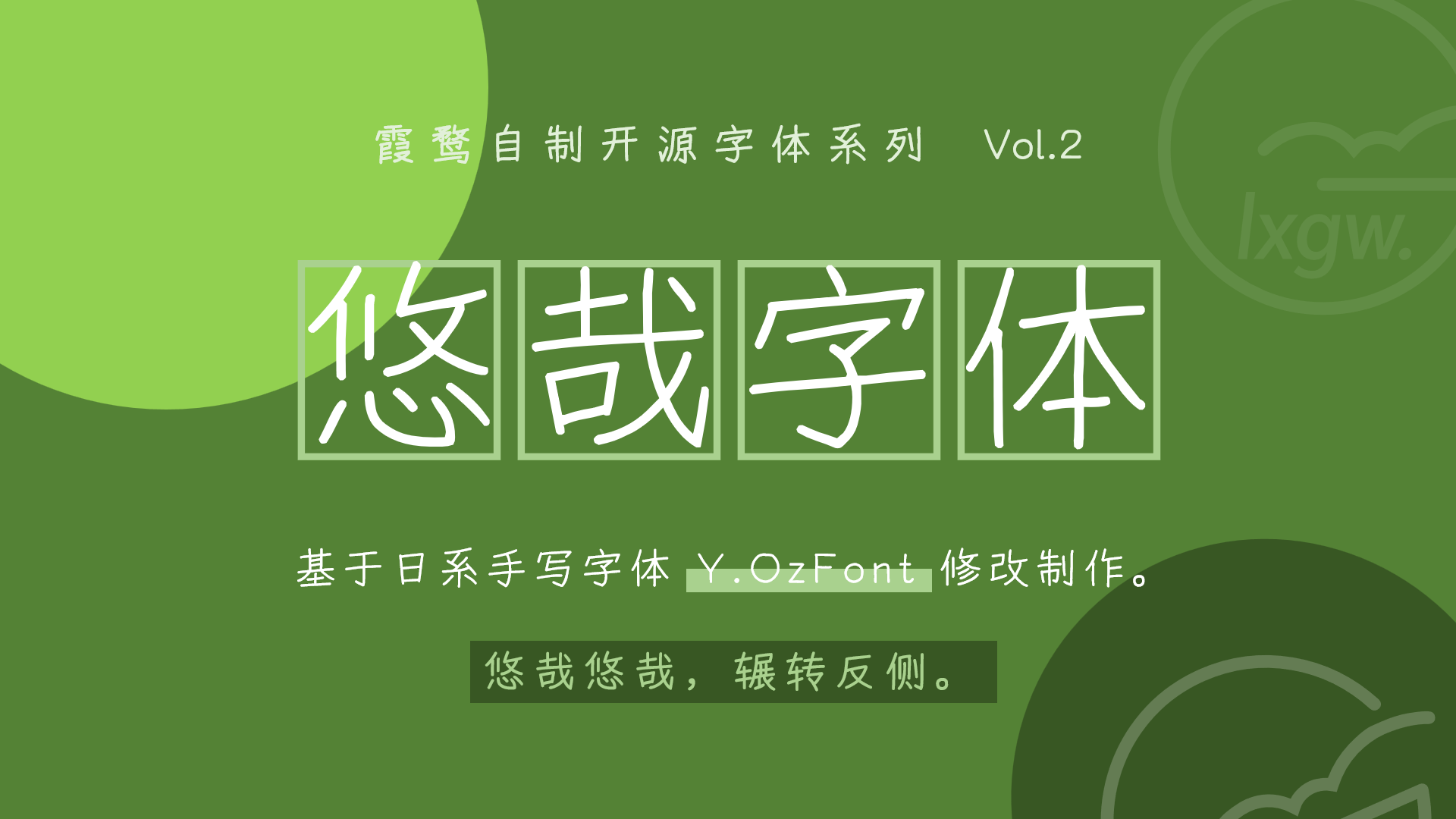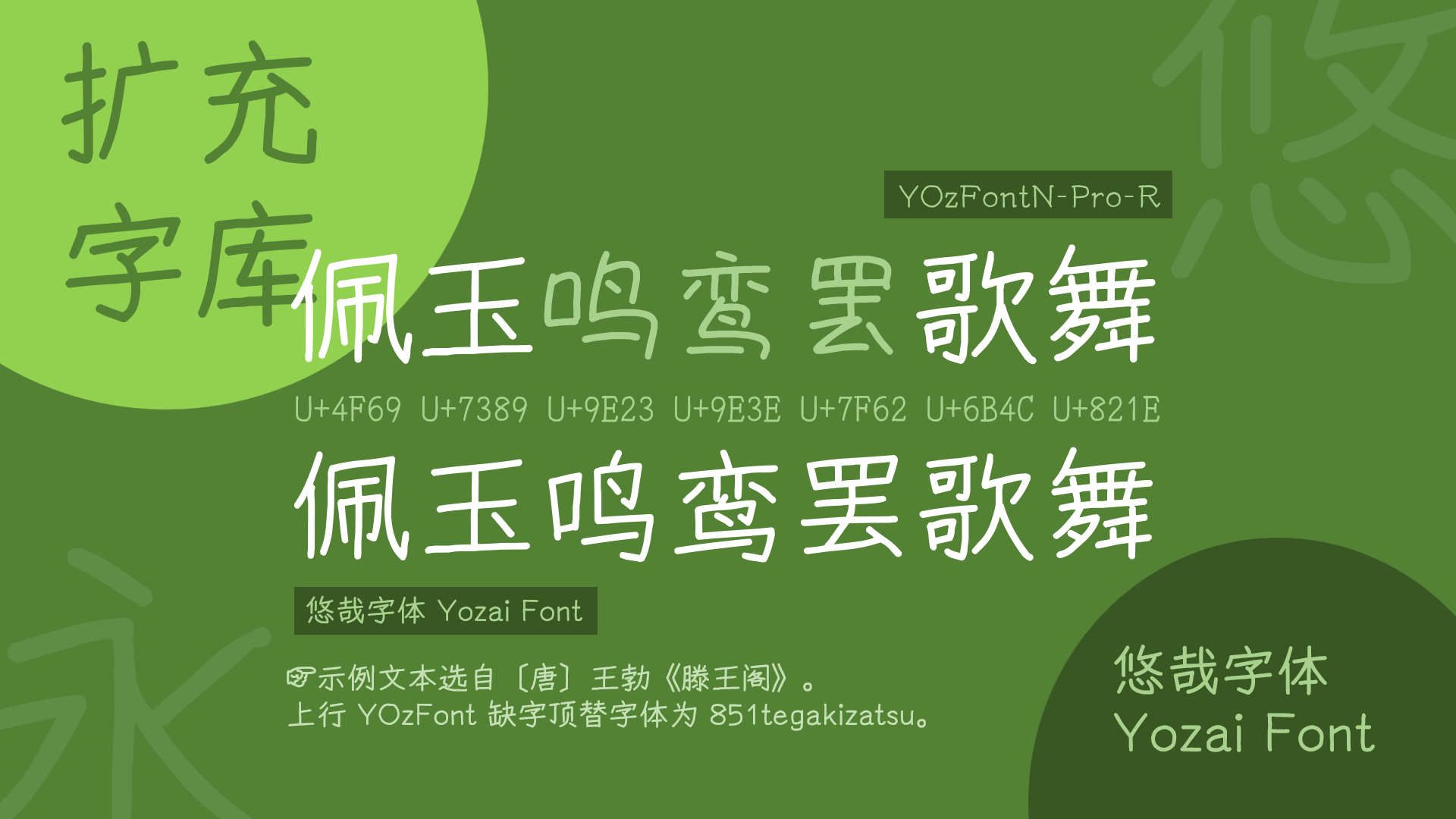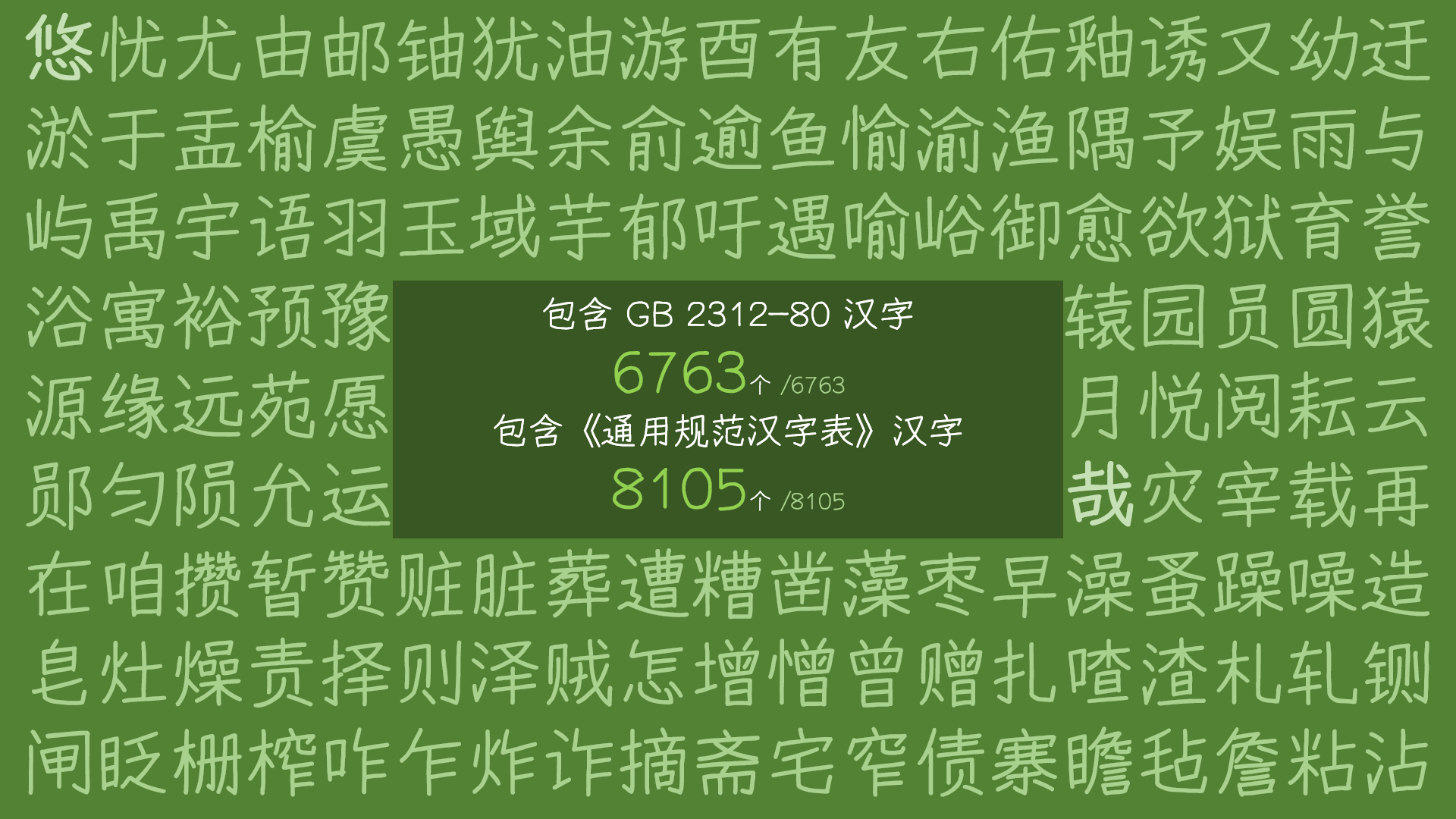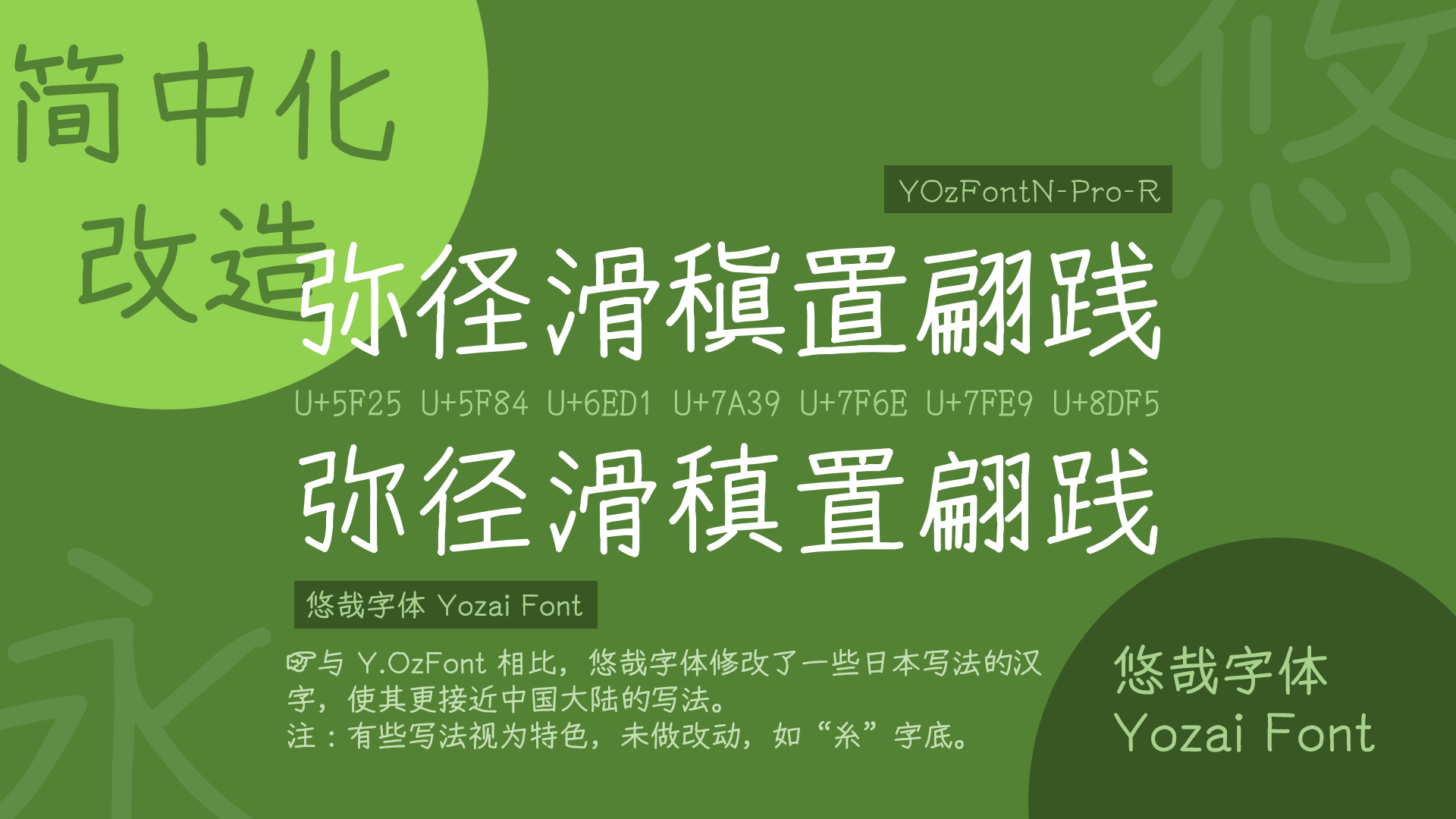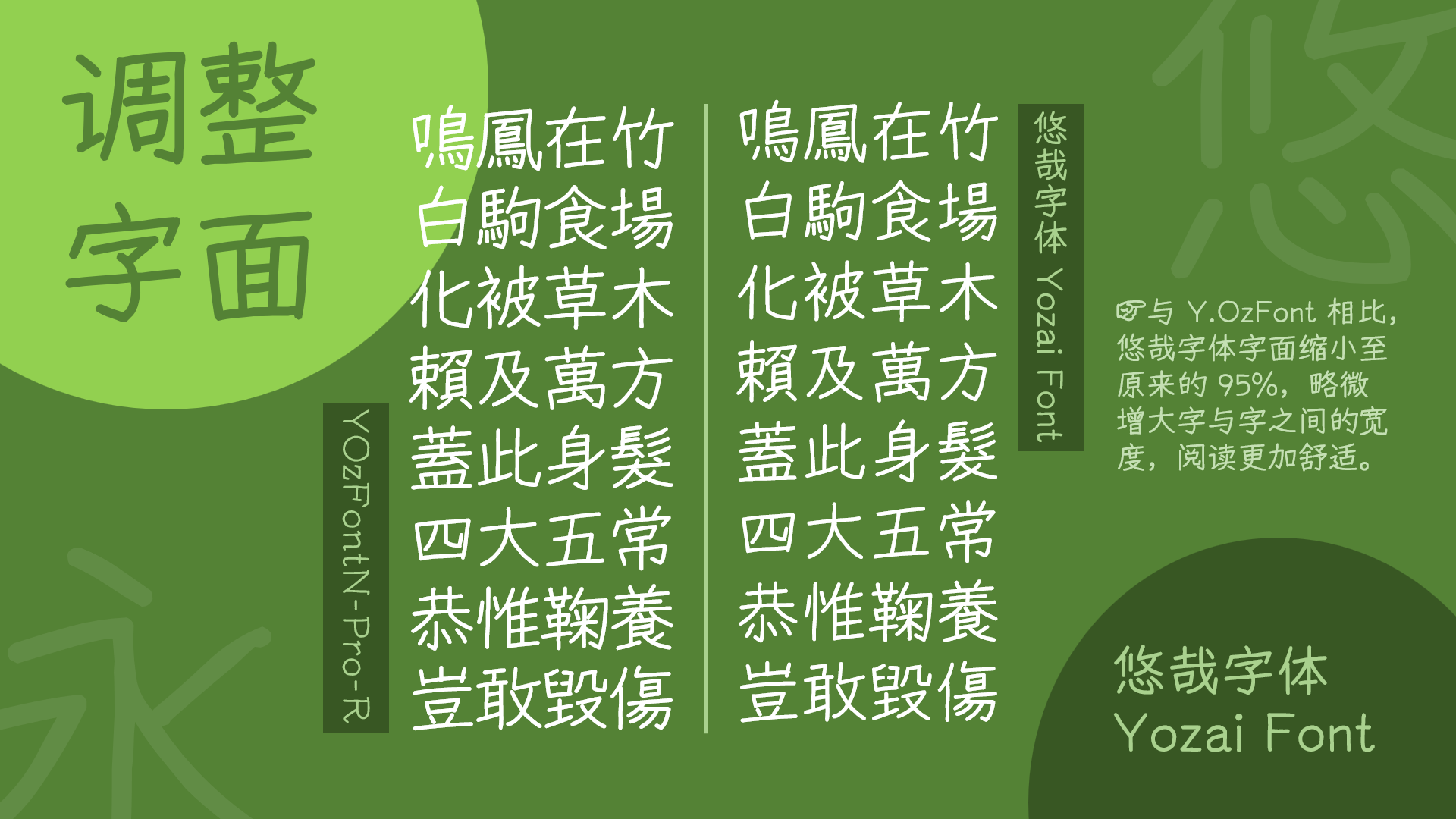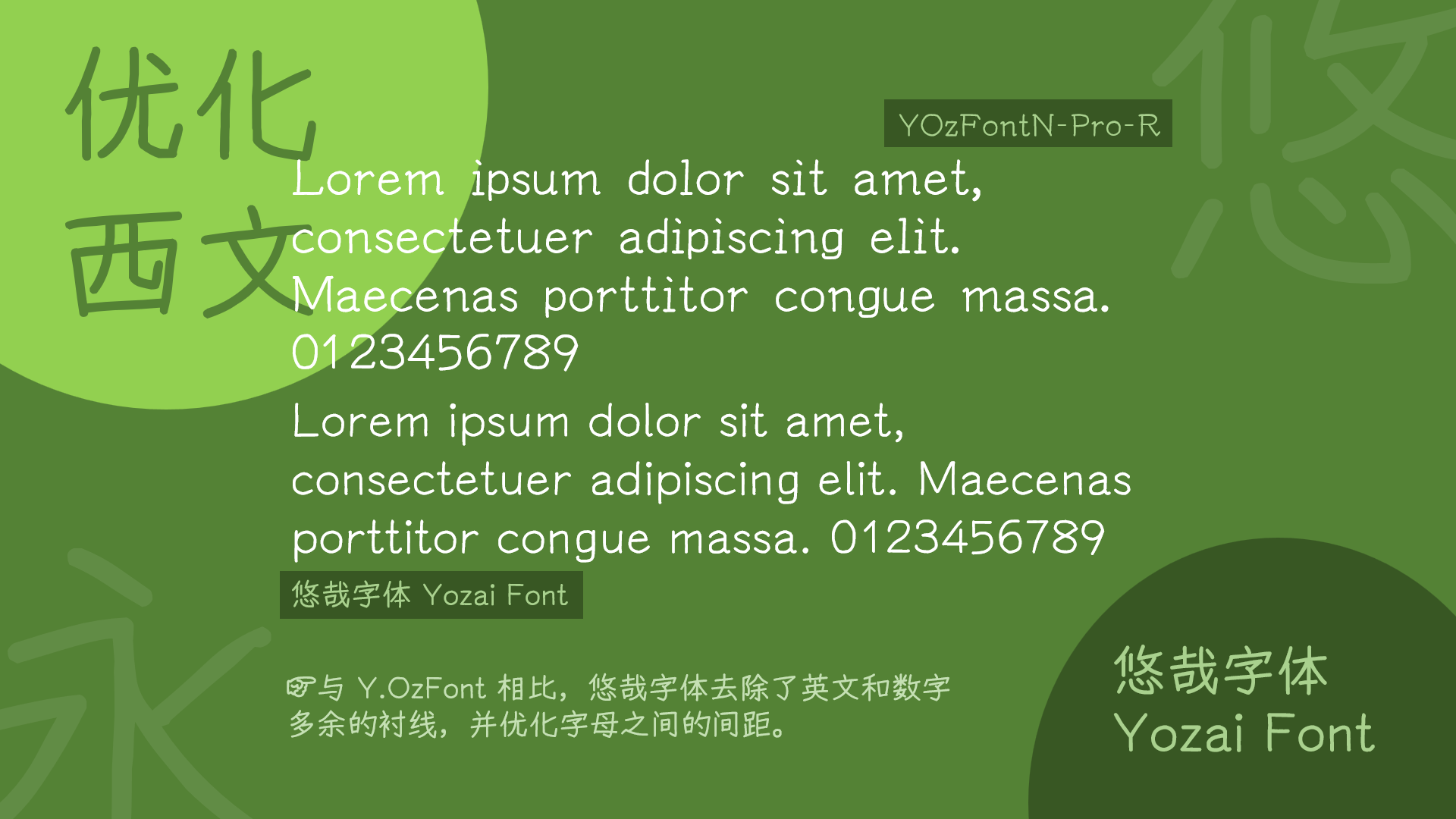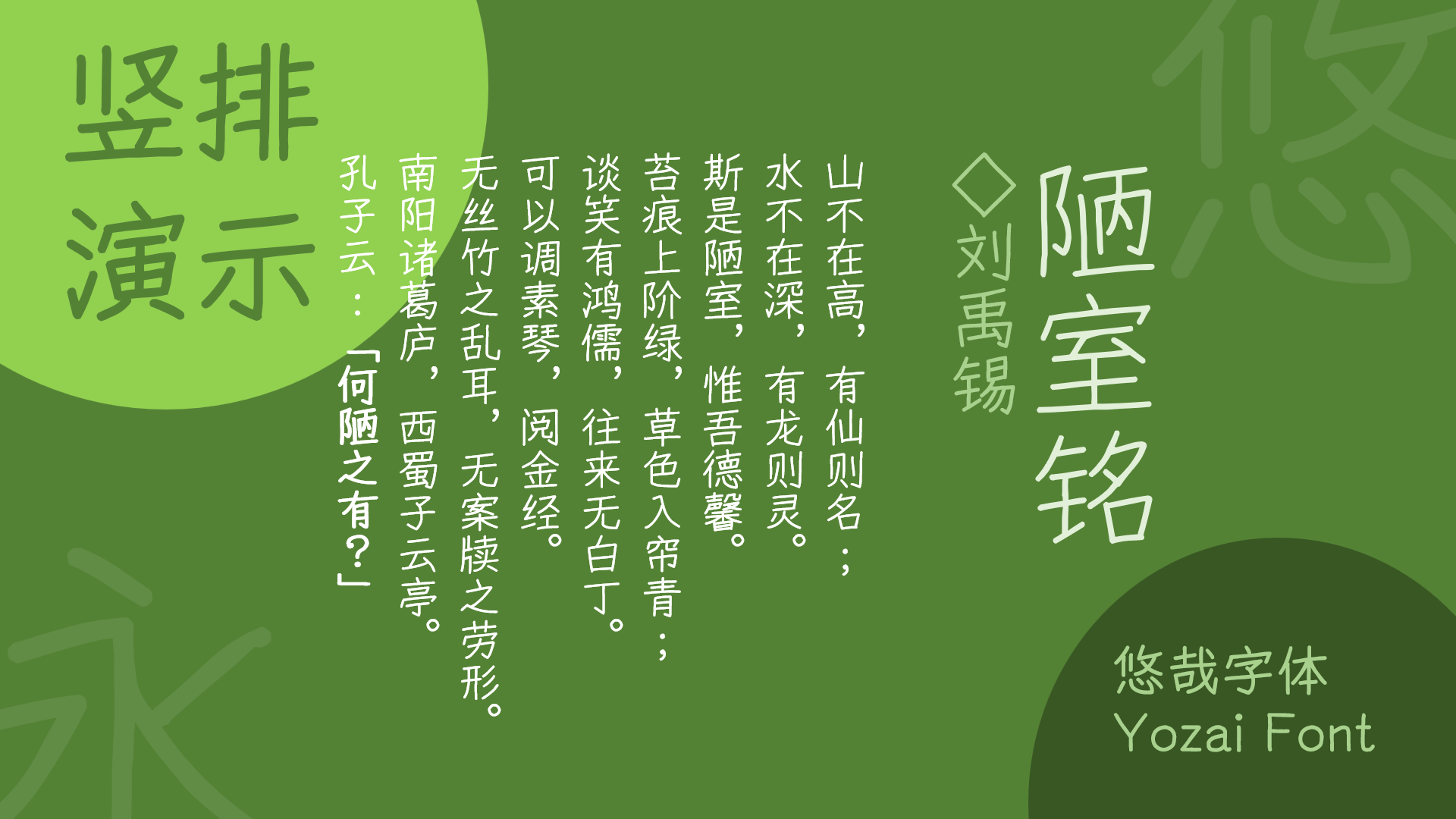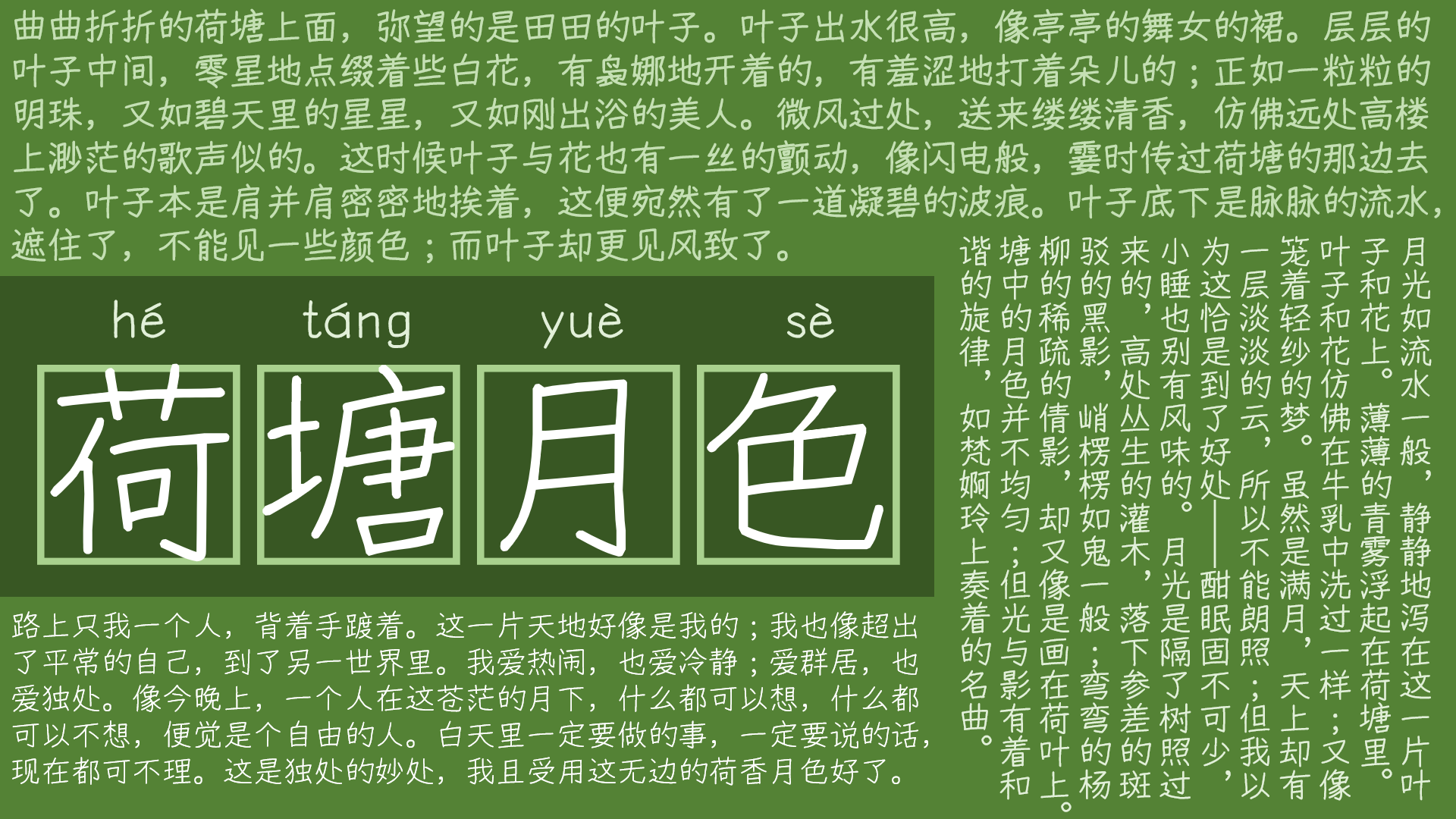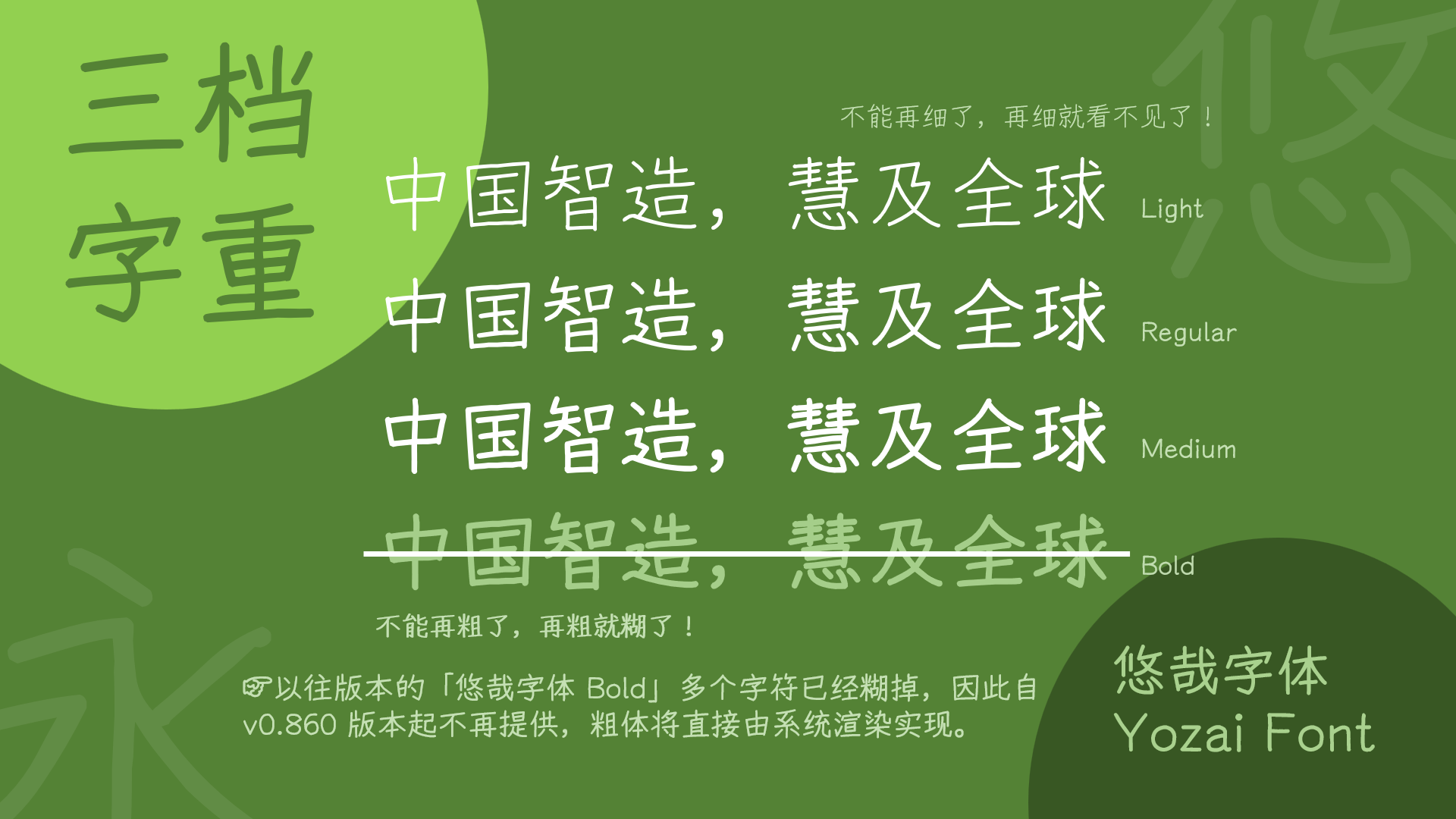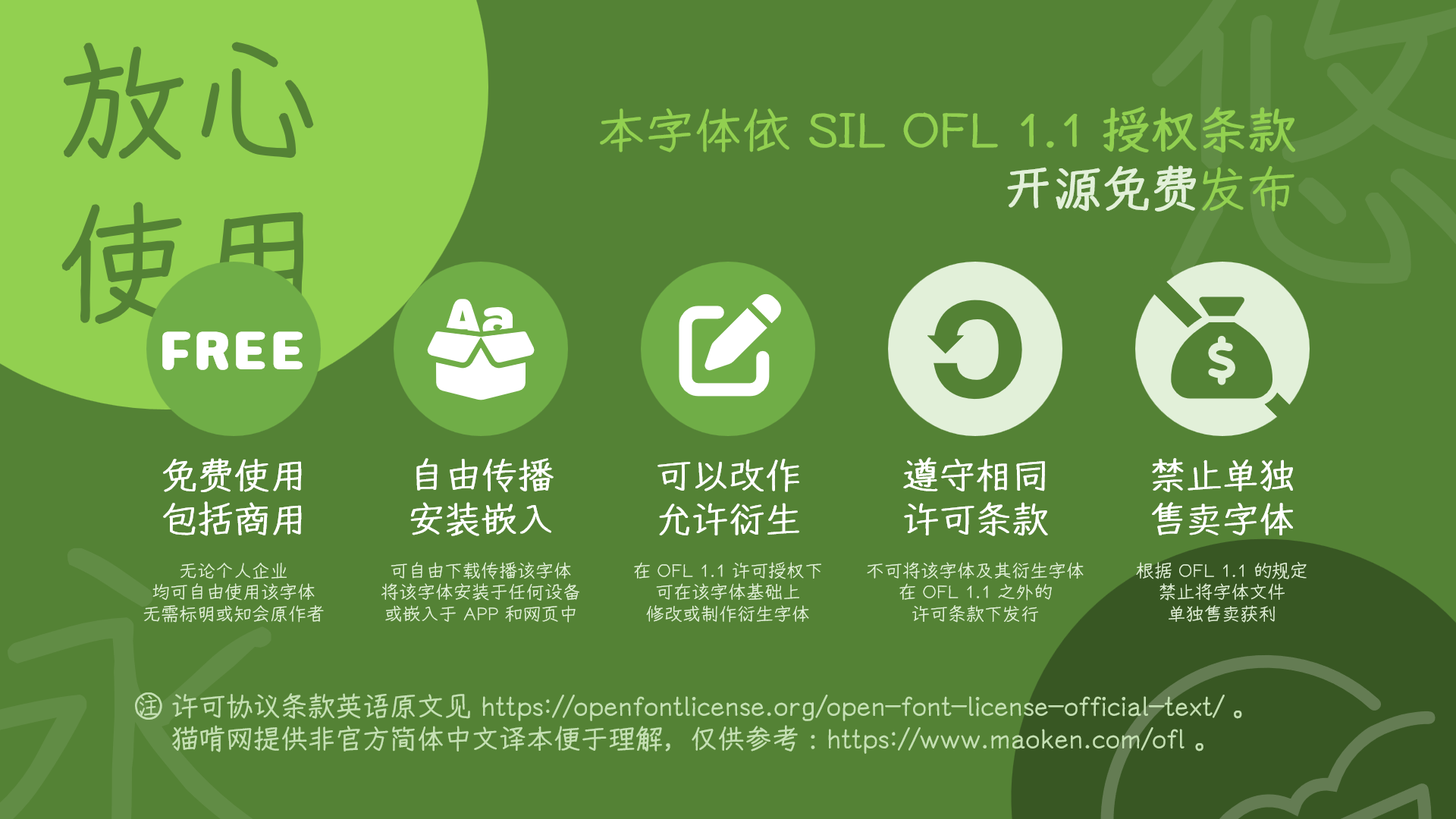
A Chinese handwriting font derived from YozFont. 一款衍生于 YozFont 的中文手写字型。
悠哉字体 / Yozai Font
A Chinese font derived from Y.OzFont. 一款衍生于 YozFont 的中文字体。
简介
本字体是一款基于 Y.OzFont 的手写风格的字体。利用原字体中已有的笔划和部件,通过拼接和调整造出新字 (必要时自己用鼠标写出部件) 。目前已补全原字体中有对应繁体字的简体字、 GB 2312 范围内的所有汉字 (6763 个) 、《通用规范汉字表》范围内的所有汉字 (8105 个) ,BIG5 范围内的所有汉字 (13058 个) 。自 0.860 版本起,采用 zi2zi 深度学习补全 CJK 统一表意文字基本区 20992 字,并按需增补少量扩展区汉字。
在原 Y.OzFont 的基础上,字面缩小至原来的 95%,优化西文和标点符号的显示;修改部分汉字的写法,使其接近中国内地的规范字形。由于原版字形偏细,从 0.715 版本起,新增 Medium (中等) 字重。
自 0.717 版本起,本字体共有 4 个字重: Light、Regular、Medium、Bold;自 0.860 版本起,Bold 字重取消。
- 本字体仍处于测试版,部分汉字还是处于日本写法,
且字库并不是很全。计划: 更正 GB 2312 内汉字的写法为中国内地的字形,补全 CJK 统一汉字基本区内的所有汉字。 - 本人并不是专业的设计师,并未考虑设计美感,所以看起来可能略丑,补进去的字与原版可能略有违和感;此外由于时间仓促,并没有多余的时间细修,部分字的部件拼接会很生硬。但聊胜于无。欢迎大家通过 Issues 反馈。